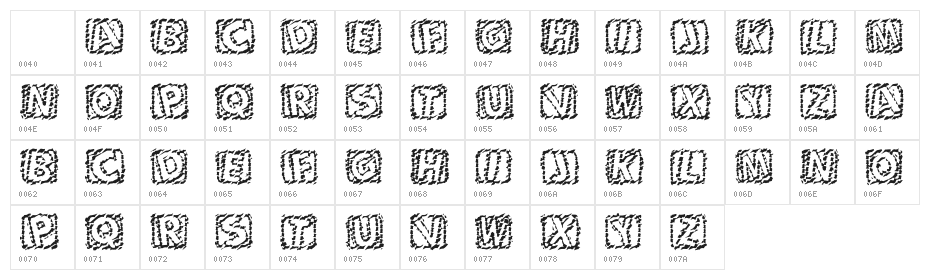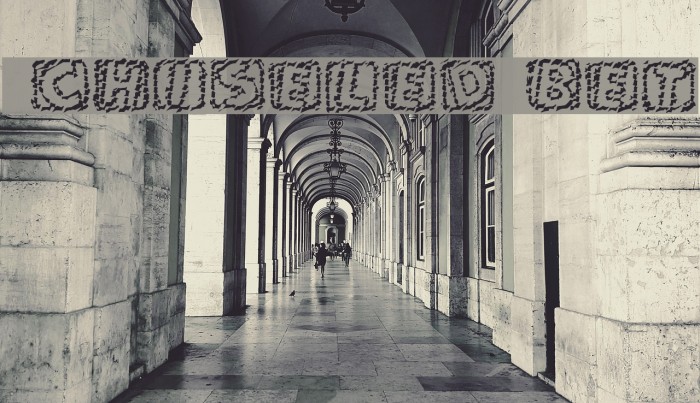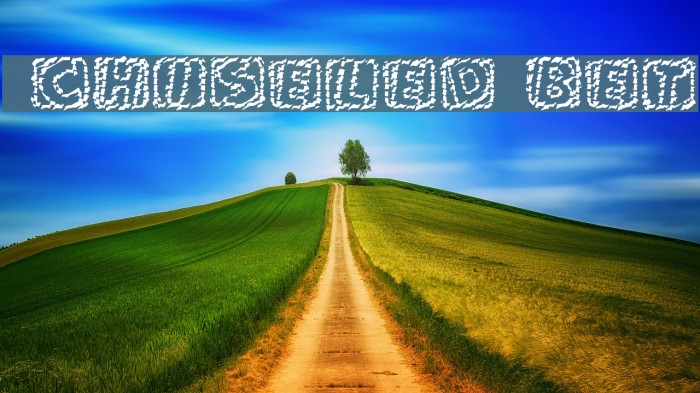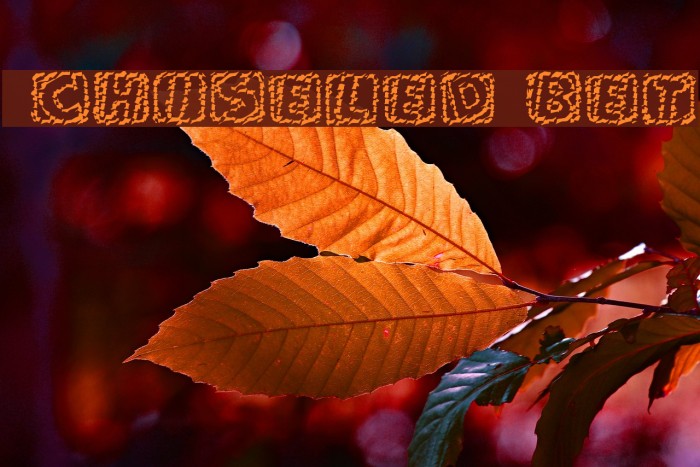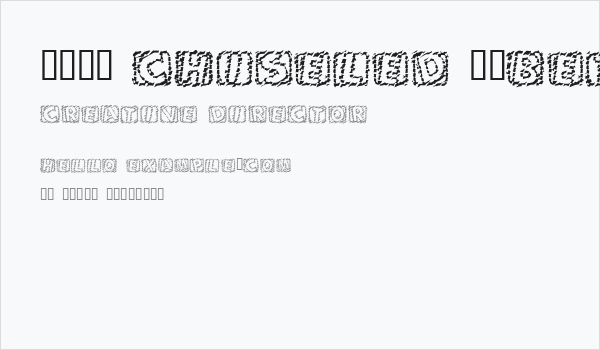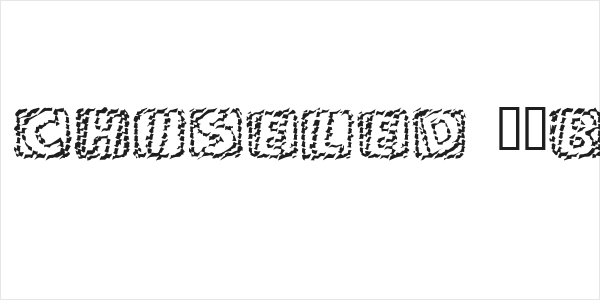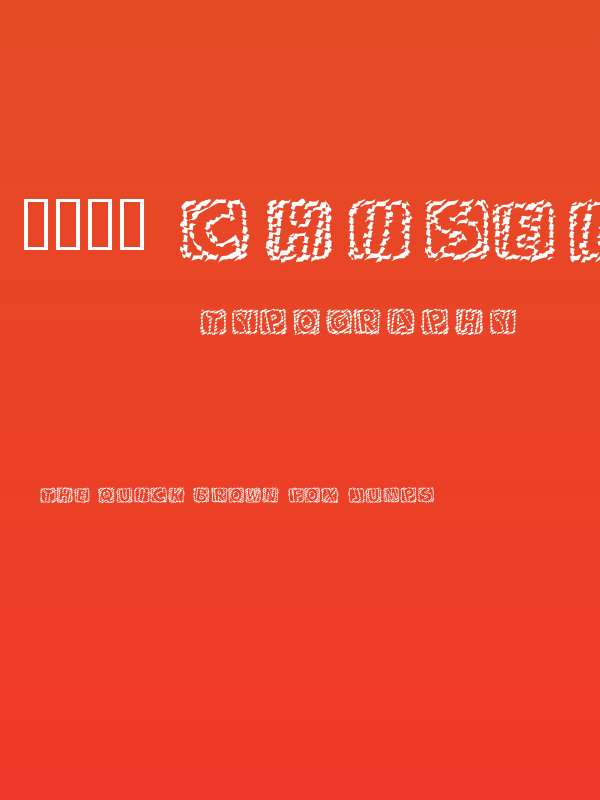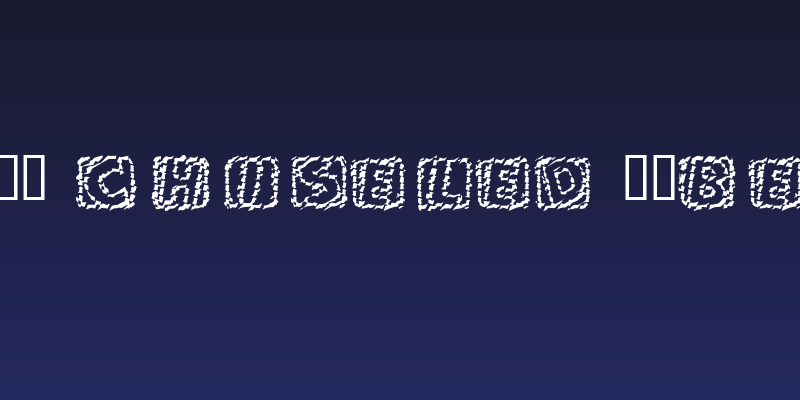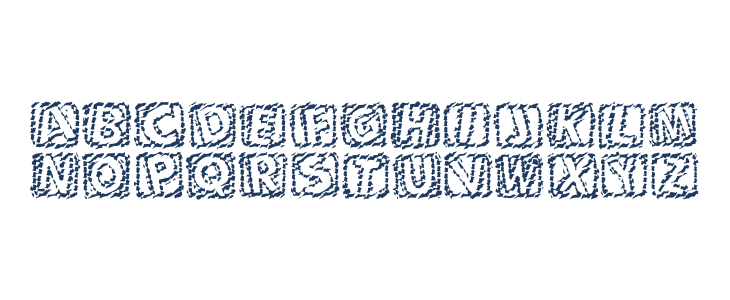
101! Chiseled 'Bet Font
✎ Messy
| Progetti proposti | Ideal for creative projects such as posters, album covers, and branding materials that require a distinctive and artistic touch. |